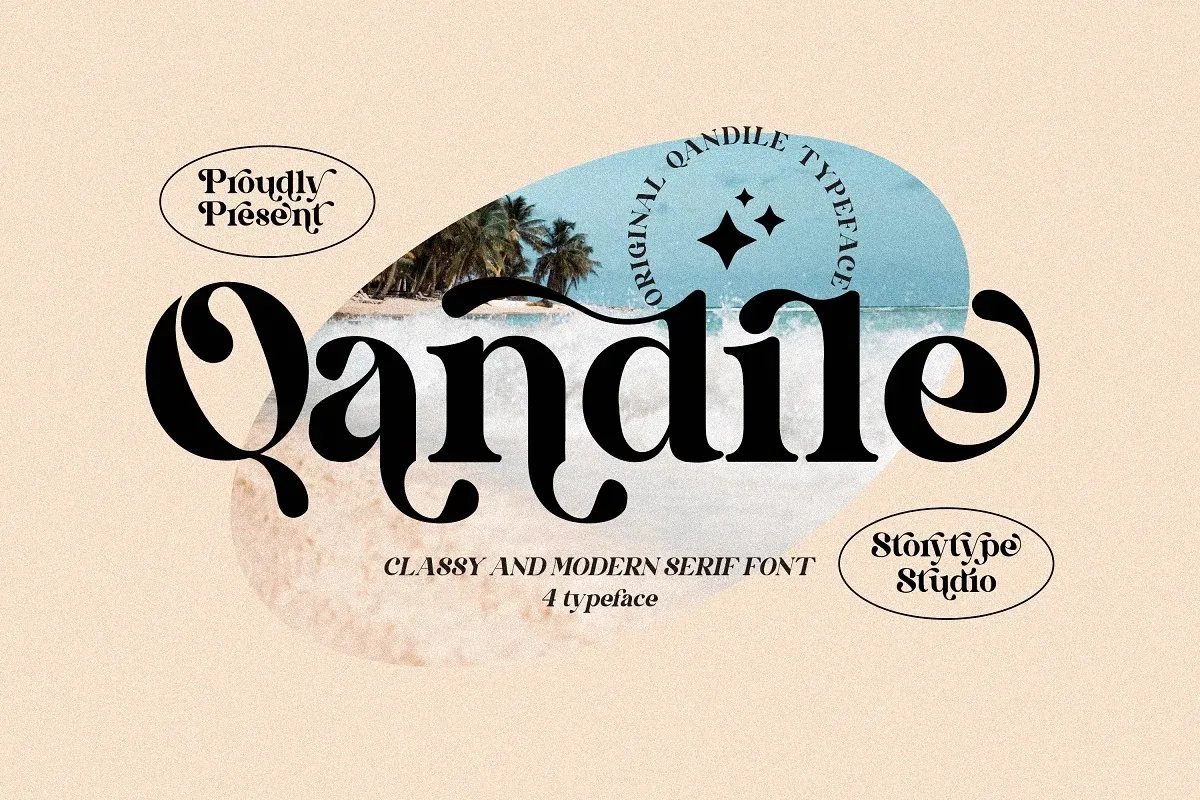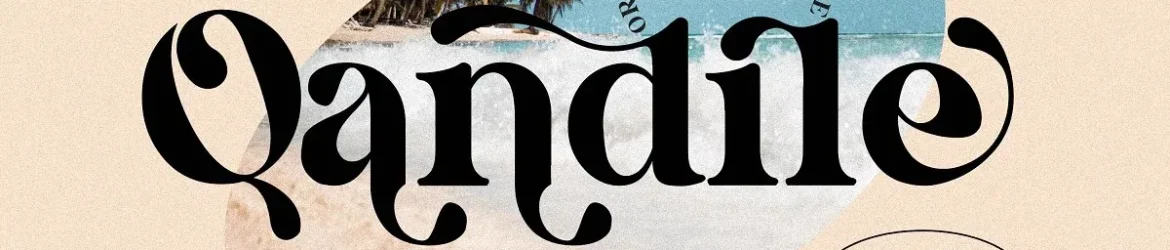
Esta fonte é uma elegante variedade de serif que oferece sofisticação simples, linhas levemente onduladas e ligaturas bonitas para criar designs únicos com um visual atraente. Perfeita tanto para grandes títulos quanto para detalhes menores, ela traz ao design uma leveza e elegância que torna qualquer projeto mais chamativo. A Qandile é perfeitamente adequada para logotipos luxuosos, títulos de livros ou filmes, marcas fashionistas, revistas, roupas, letras, frases e muito mais. Sua versatilidade permite que você use a fonte em qualquer aplicação visual, tornando-a uma ótima escolha para quem busca adicionar um toque único e sofisticado às suas criações.